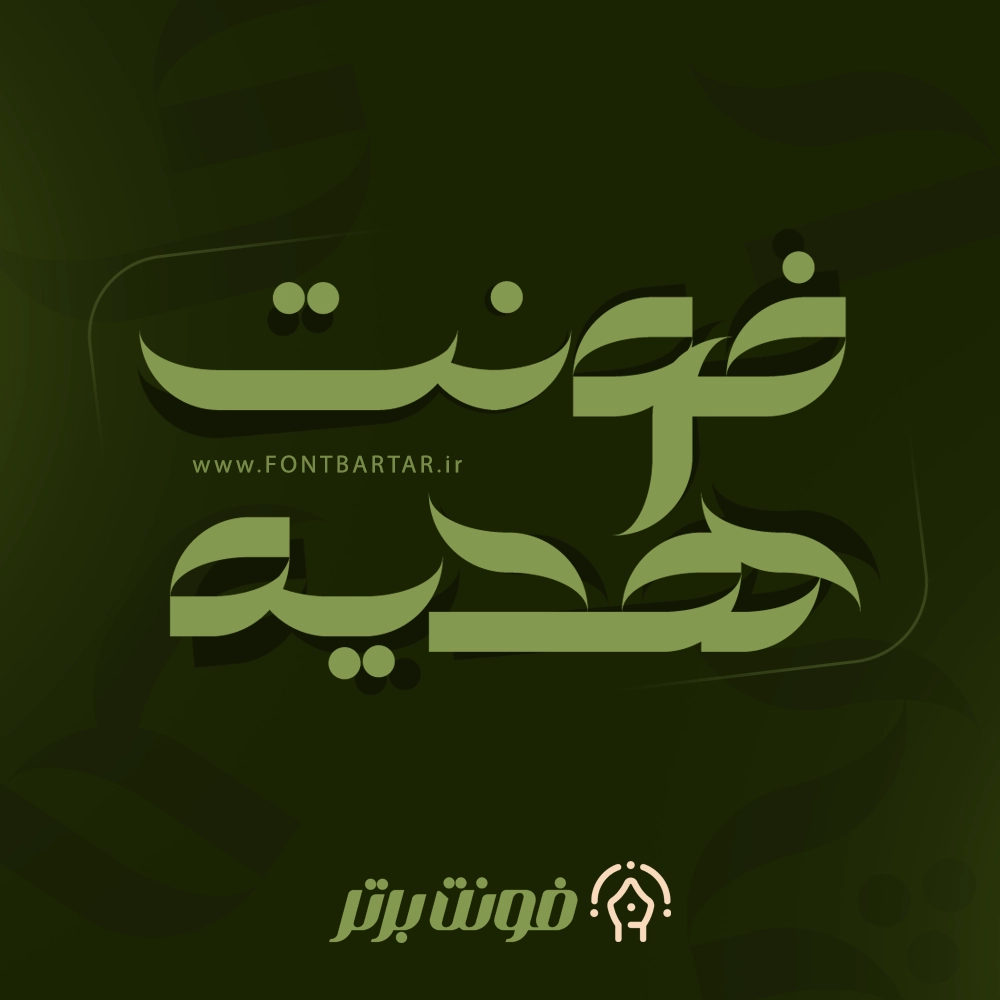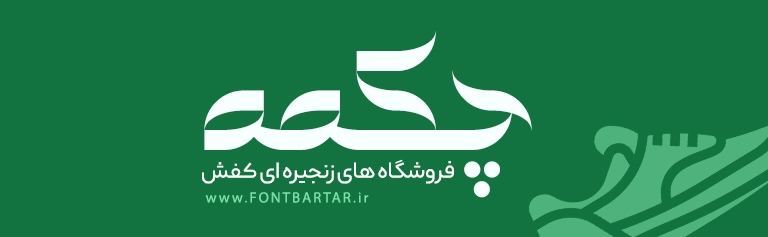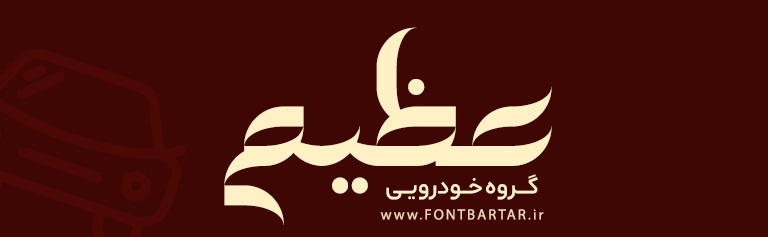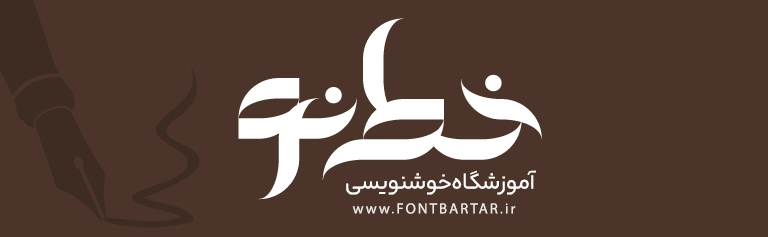
فونت هدیه | دانلود فونت خاص فارسی هدیه برای طراحی حرفهای
اگر به دنبال یک فونت خاص ، منحصرب فرد و چشمنواز برای طراحی لوگو یا تایپوگرافی فارسی هستید، فونت هدیه یکی از بهترین گزینههاست. فونت خاص فارسی با ترکیبی از سبک مدرن و اصالت خوشنویسی ایرانی طراحی شده و ظاهری جذاب، متفاوت و خوانا دارد.
فونت خاص هدبه مناسب طراحانی است که میخواهند برند و طراحی خود را متمایز کنند و به آن هویت بصری قوی ببخشند.
ویژگی های با فونت خاص هدیه
- ✅ طراحی نرم و متعادل با ترکیب سنت و مدرنیته
- ✅ پشتیبانی کامل از حروف فارسی و عربی
- ✅ مناسب برای طراحی لوگو، پوستر و بستهبندی
- ✅ وضوح بالا در نسخه چاپی و دیجیتال
کاربرد فونت هدیه در طراحی
فونت هدیه برای طراحانی ساخته شده که به دنبال زیبایی و معنا در اثر خود هستند. از این فونت میتوانید در زمینههای زیر استفاده کنید:
- طراحی لوگوهای فارسی با حس حرفهای و گرم
- ساخت تیترهای تبلیغاتی و فرهنگی
- طراحی پوستر، جلد کتاب و پستهای شبکههای اجتماعی
- تولید محتوای بصری برای برندهای ایرانی
چرا فونت هدیه را انتخاب کنیم؟
زیبایی بصری در دنیای طراحی، همان چیزی است که برند شما را از دیگران متمایز میکند. فونت هدیه با ساختار متوازن و فرم نرم خود، باعث میشود طراحی شما:
- حس هنری و حرفهای منتقل کند
- در نگاه اول توجه کاربر را جلب کند
- با هر نوع پسزمینه و رنگ هماهنگ شود
1. فونت هدیه برای چه نوع طراحیهایی مناسب است؟
فونت هدیه برای طراحی لوگو، پوستر، جلد کتاب، تایپوگرافی و طرحهای فرهنگی یا هنری عالی است.